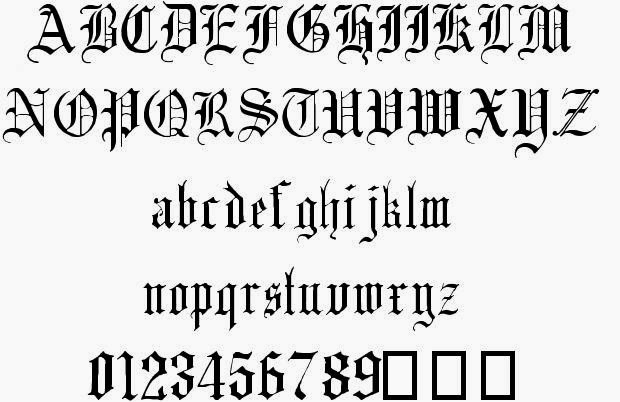
Готический шрифт. Пошаговые уроки — Часть 1. i, l, n, u, c, e
Эта статья начинает серию пошаговых уроков по готической каллиграфии. Здесь я не буду давать буквы в алфавитном порядке. Легче и быстрее начать с простых форм и переходить к более сложным. Большинство элементов разных букв повторяются, поэтому вы всегда будете отталкиваться от того, что уже знаете.
В этом уроке мы рассмотрим буквы: i, l, n, u, c, e.
Во втором уроке изучим: m, w, r, t, h, b, f, k, o, q, p, v.
В третьем уроке будут: d, g, z, x, j, y, a, s.
Четвертый урок расскажет как писать прописные буквы готического алфавита.
Можно найти много иллюстраций того, как должны выглядеть буквы готического алфавита. Ниже я приведу пример того, что мы будем изучать.
Может быть это не самый красивый пример готической каллиграфии, но он дает отличное представление об этом шрифте.
И так, приступим.
Сетка для готического шрифта
Высота букв зависит от ширины пера. В готическом шрифте для строчных букв обычно используется строка высотой 4.
5 ширины пера. Это справедливо для букв «x», «e», «c», «a», «o». Буквы с выносными элементами, такие как «b», «h», «g», «p» имеют высоту 7 ширин пера. Буквы «d» и «t» могут иметь в высоту от 4.5 до 7 ширин пера.
Чтобы померить высоту строки пером достаточно нарисовать лесенку или штрихи в шахматном порядке. Например, вот как выглядит строка высотой четыре пера.
Можно рисовать сетку от руки, а можно сгенерировать с помощью специальных сервисов и распечатать. Как это делается я написал здесь.
Когда вы определитесь с высотой своих букв и подготовите сетку можно начать практику. Начнем с букв «i» и «l». Ниже я привел схему как строятся эти буквы:
Верхняя строка иллюстрации показывает как пишутся элементы буквы по отдельности, на нижней строке – как они выглядят вместе. Конечный результат обведен золотым прямоугольником.
Убедитесь, что держите перо свободно, под углом 45º и начинайте писать.
Готическая «i» состоит из трех частей – это симметричный ромб сверху, короткий вертикальный штрих в середине и второй симметричный ромб снизу, который имеет дополнительный хвостик вверх, если это не последняя буква в слове.
Тонкий косой штрих над «i» не всегда встречается в средневековых образцах, но он делает письмо более разборчивым.
Готическая буква «l» пишется почти так же, как «i», только верхний ромбик ставится на высоте семи ширин пера от базовой линии. Буква «l» выше «i» на две ширины пера.
Во время письма избавляйтесь от мышечного напряжения и плохой осанки. Они сделают ваше письмо жестким и неуклюжим. Расслабьте руки и выпрямите спину, не сжимайте ручку пера так, чтобы суставы побелели. Старайтесь двигать всей рукой от запястья до предплечья, не нужно писать только движением пальцев.
Повторяйте каждую букву по несколько раз, стараясь каждый раз улучшить их форму. В начале я писал по одному — два листа в день каждой буквы, чтобы отработать их форму и довести движения до автоматизма.
Слов, содержащих только буквы «i» и «l» не так уж и много, но я рекомендую практиковаться на следующем: li ill illi lili.
Следующие готические буквы, которые мы изучим будут «n» и «u».
Они состоят из двух букв «i», соединенных вместе диагональным хвостиком. Расстояние между вертикальными штрихами должно быть 1.5-2 ширины пера. А соединительный хвостик у «n» вверху и у «u» внизу должен лишь соединять эти штрихи по диагонали.
Буквы «n» и «u» состоят из шести последовательных штрихов. Это может показаться слишком сложным и кропотливым, но чем больше вы будете практиковаться, тем легче и быстрее у вас будут получаться красивые готические буквы.
Когда отработаете формы этих букв по отдельности приступайте к написанию следующих слов. Они будут выглядеть потрясающе:
nun lull nil null inn lulu
Отлично! Теперь перейдем к двум менее сложным буквам – «c» и «e». Каждая содержит всего два штриха пером. Вам нужно всего лишь изменить направление каждого штриха примерно посередине, не делая изгибов.